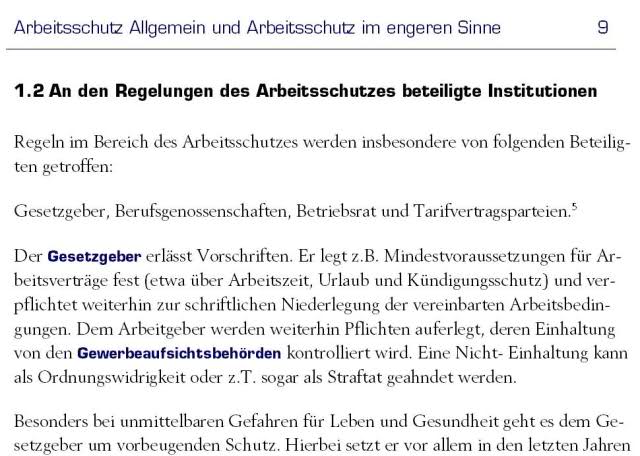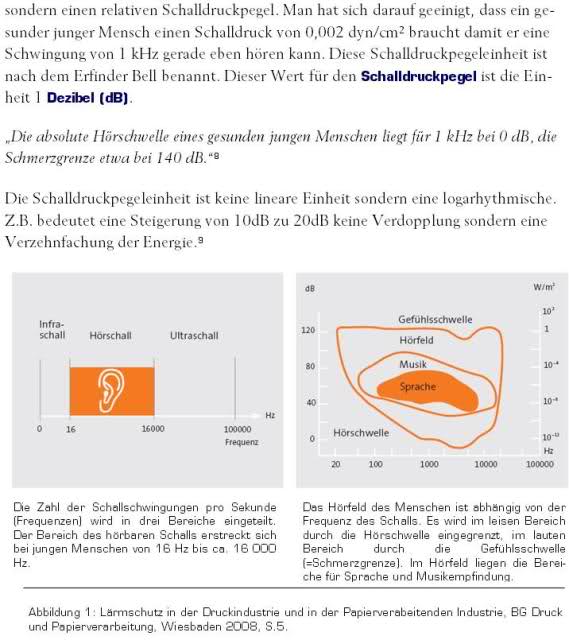
Berling und Eurostile für eine Diplomarbeit?
Ich schreibe zur Zeit eine Diplomarbeit und bin gerade dabei Schriftarten auszuwählen. Ein Bekannter hat mir nun empfohlen für den Textkörper Berling zu nehmen und für Überschriften Eurostile. Ich habe die Schriften bereits erworben (Berling nur die normale und Eurostile noch mit bold, italic, und italic bold). Ich bin nun aber doch unsicher geworden, ob sie wirklich so gut zusammenpassen. Mich würde sehr Eure Meinung interessieren.
Besonders zu den hervorgehobenen Wörtern. Ich habe einige wichtige Wörter hervorgehoben, indem ich sie in Eurostile bold und in dunkelblau darstelle. Durchbricht das zu sehr den Textfluss?
Berling verwende ich für den Textkörper, Eurostile verwende ich für Überschriften, Seitenüberschriften, Beschriftungen bei Bildern und Tabellen, sowie für den Fußnotentext.
Die Seiten werden später in einer Druckerei einseitig auf A4 gedruckt.
Welche Schriftgrößen würdet Ihr nehmen?
Was haltet Ihr von Blocksatz für solch längere Arbeiten?
Als Beispiel habe ich ein Bild hinzugefügt.
unabhängig von den verwendeten Schriften sieht das Ganze im Moment sehr unruhig und meines Erachtens auch nicht sehr ansprechend aus. Im Moment sind die Hierarchien auf der Seite nicht klar verteilt, beinahe jedes Element konkuriert um die Aufmerksamkeit. Die Hervorhebungen sind quasi dreifach ausgezeichnet, in einer anderen Farbe, in einer anderen Schrift und auch dazu noch fett. Warum muß hier ausgezeichnet werden? Würde eine passive Auszeichnung ausreichen oder sollen die Stichwörter wirklich sofort ins Auge fallen? Das sind Fragen, die Du Dir hier stellen mußt. Im Zweifelsfall würde ich versuchen, eine oder höchstens zwei der Auszeichnungsmöglichkeiten gleichzeitig einzusetzen.
Nach der Kapitelbenummerung zu urteilen (die ich übrigens auf den Tod nicht leiden kann, weil ihr m.E. heutzutage jeder Sinn fehlt) ist das eine Überschrift der 2. Ebene. Wieviele Ebenen hast Du insgesamt? Diese Überschrift ist dicht (m.E. zu dicht) an der Textgröße und nur durch den fetten Schnitt ausgezeichnet. Dadurch hebt sie sich zwar vom Text noch gerade ganz gut ab, im Moment kommt es aber zu einer Konkurrenz mit dem lebenden Kolumnentitel, da dieser durch Größe und Farbe Aufmerksamkeit auf sich zieht.
Blocksatz ist bei längeren Zeilen an und für sich kein Problem, gerade in Deutscher Sprache schreit es allerdings nach anständiger Silbentrennung. Und werden die Zeilen kürzer, wie z.B. bei Deiner Bildunterschrift auf der rechten Seite, dann siehst Du sofort die riesen Lücken, die in den Text gerissen werden. Der Satz wäre mir Persönlich allerdings zu eng, ich würde den Zeilenabstand aufbohren.
Weitere Kleinigkeiten: Die Linie zur Abgrenzung der Fußnoten klebt an den Bildunterschriften, während die Linie unter dem lebenden Kolumnentitel zu weit entfernt ist.
Dezibel als Einheit sollte, wenn ich mich nicht irre, genau so einen geschützten Leeraum bekommen wie kHz oder dyn/cm² auch. Außerdem werden nach einem Punkt keine Abkürzungen (»Z.B.«) verwendet sondern diese ausgeschrieben.
Was nun die Schriften angeht: Die Berling gefällt mir auf den ersten Blick gar nicht so schlecht, scheint mir aber mit großen Problemen bei der Zurichtung daher zu kommen. Zumindest auf dem Bild erscheint mir der Satz recht fleckig, die Buchstabenabstände z.T. recht unregelmäßig und der ausgeprägte f-Bogen schreit nach dem Einsatz von Ligaturen. Wenn das kein Problem ist, dann, so finde ich, kann man die ruhig nehmen, wenn Du Dir den Aufwand sparen möchtest, dann nimm eine Schrift, die einfacher zu handhaben ist (in welchem Programm arbeitest Du übrigens?).
Zur Eurostile möchte ich eigentlich nichts sagen, sie liegt mir einfach nicht. Ich würde sie nicht verwenden, schon gar nicht in so prominentem Maße, aber dazu sollen lieber die Profis mehr sagen … :twisted:
@Tholaris: Welches Programm verwendest Du um die Diplomarbeit zu erstellen, nur mal so aus Interesse.
Nach der Kapitelbenummerung zu urteilen (die ich übrigens auf den Tod nicht leiden kann, weil ihr m.E. heutzutage jeder Sinn fehlt) [...]
Kannst Du mir das erklären?
Erst mal die einfache Antwort. Ich benutze Word. Ich weiß, dass ich mich in Latex oder so einarbeiten sollte, aber mit um die 100 Seiten wirds wohl mit Word klappen.
Word? :shock: Viel Glück dabei :D . :tutor: Es heißt LaTeX. Und die Einarbeitung in LaTeX kann sich auch lohnen. Das kommt raus, wenn man mit Word arbeitet.
Und wenn du nicht gerade LaTeX verwenden willst, nimm irgendwas anderes aber Word, das ist gerade mal gut genug für einen Brief, obwohl da gibts ja scrlttr2 :D , und für irgendwelche fixen Sachen. Obwohl ich den Text ja eigenlich nur in die Vorlagedatei eingeben muss, sofern ich mir denn eine erstellt habe, von der Geschwindigkeit des Schreibens läuft es also auf das Gleiche hinaus, jedoch hab ich die LaTeX-Datei schneller fertig, da ich nicht erst noch alles zusammenklicken muss. Außerdem geht ja der Absatzalgorithmus von Word schon mal gar nicht. Blocksatz und Silbentrennung von Word ein Witz: http://www.typografie.info/typoforum/viewtopic.php?f=8&t=5997, TeX hat einen tollen Mehrzeilensatzalgorithmus mit schönem Blocksatz. Das einzige Problem ist bloß, leider die Fonteinbindung, aber dafür gibt es ja Xe(La)TeX, welches allerdings noch nicht eine volle Mathematik-Unterstützung hat, und nicht mit microtype.sty zusammenarbeitet (kein optischer Randausgleich)
Mal langsam ... wenn's bei einer Arbeit mit 100 S. bleibt, dann geht's auch mit Word. Nur nicht entmutigen lassen ...
Also ein Kurs Typo für Anfänger samt Programmschulung hast du schon von den Kollegen bekommen. Aber die Eurostile ist keine echte Schrift. Sie sieht nicht mal so aus. Profis arbeiten damit nicht. Alternativen sind dir schon genannt. Die Auswahl ist ziemlich groß. Aber Überschriften aus der selbe Schrift wie der Bodycopy, eine bisschen fetter und größer, reichen aus (für eine Diplomarbeit).